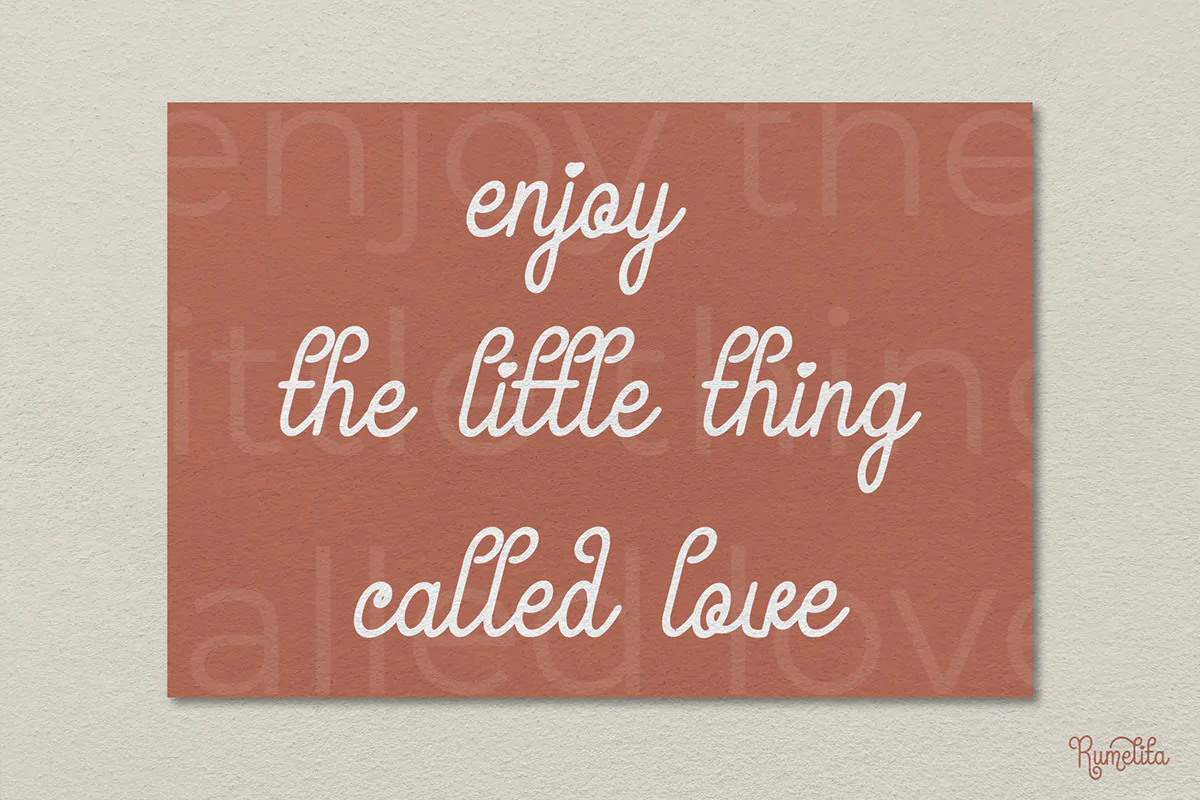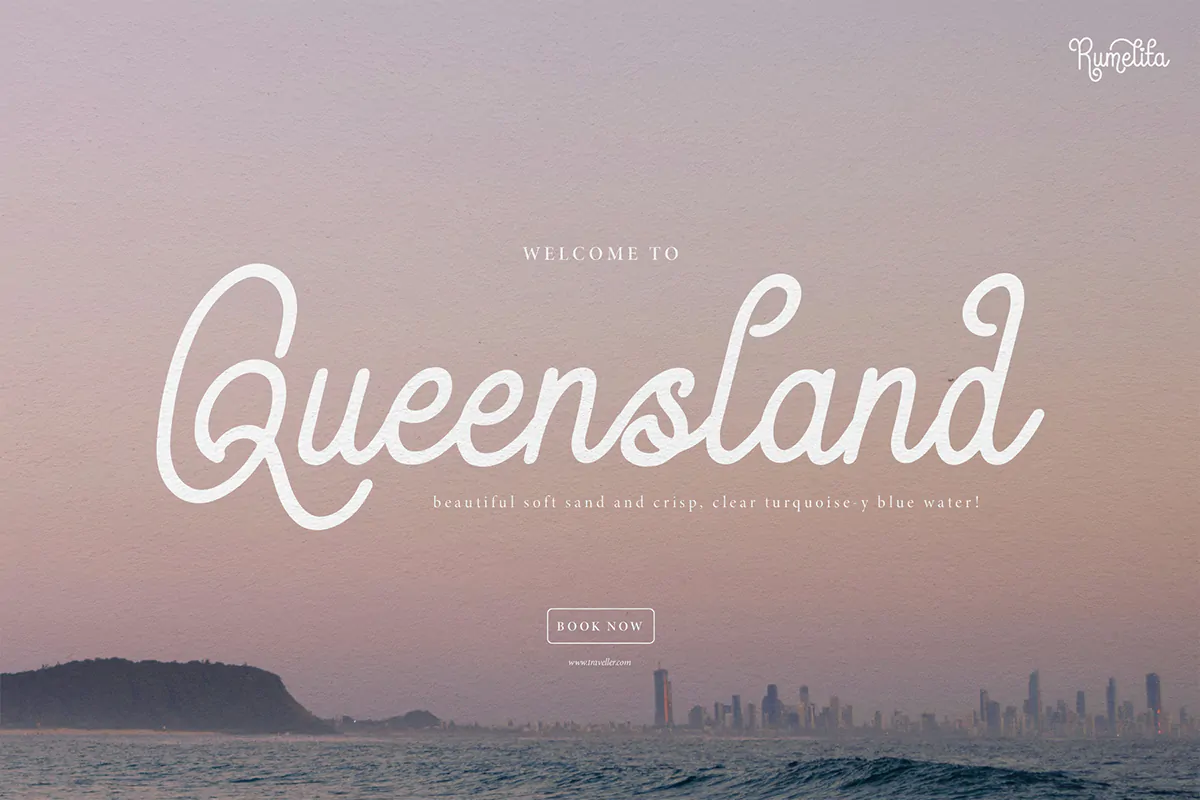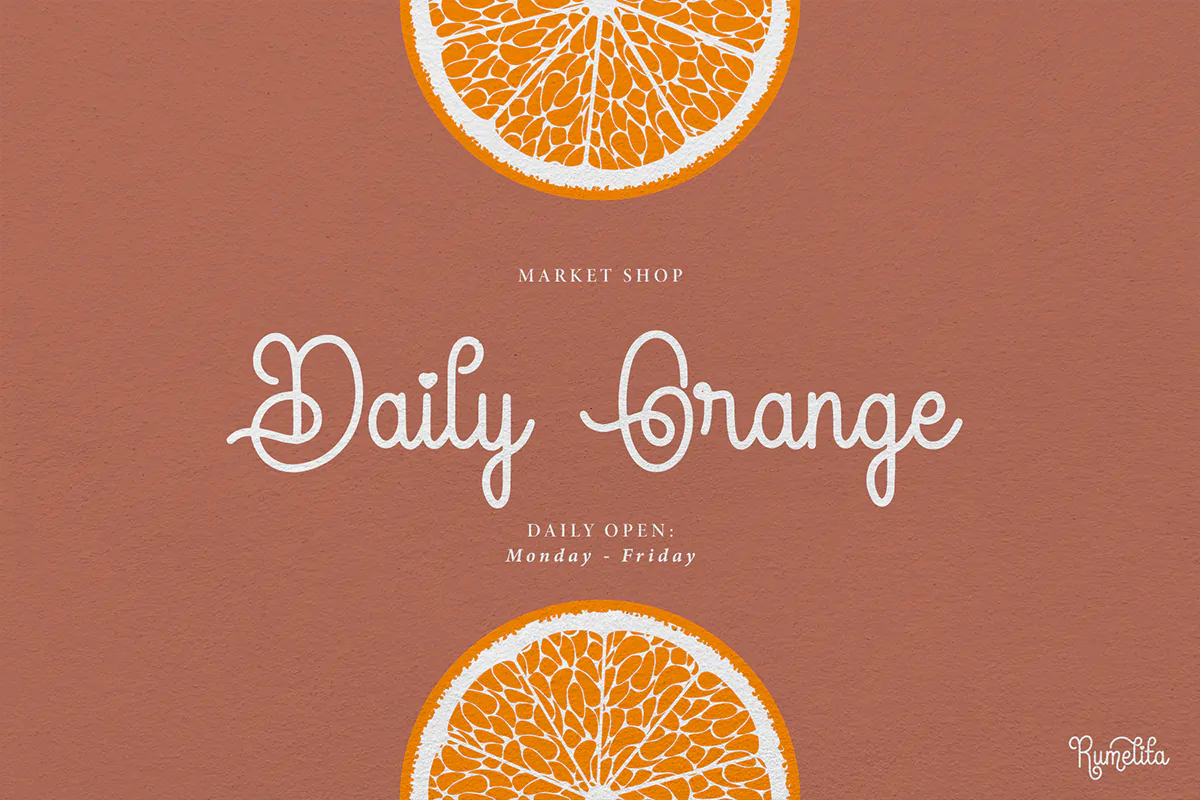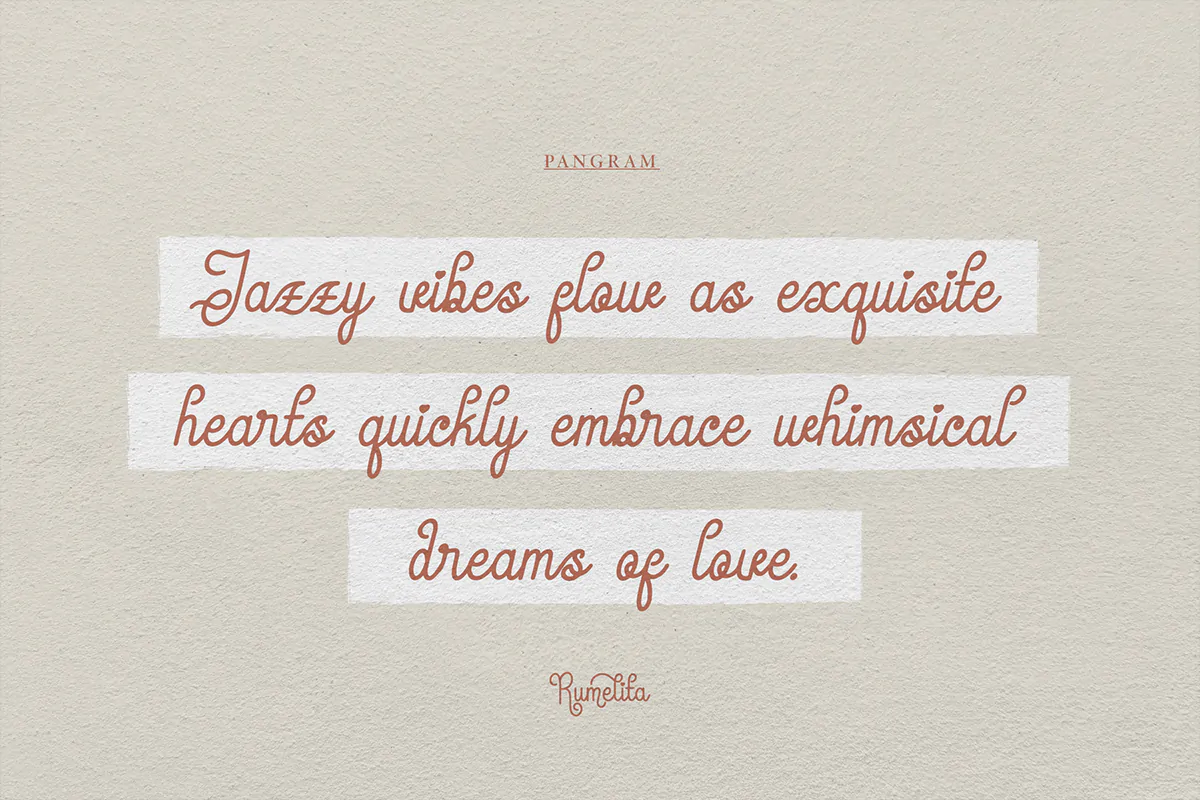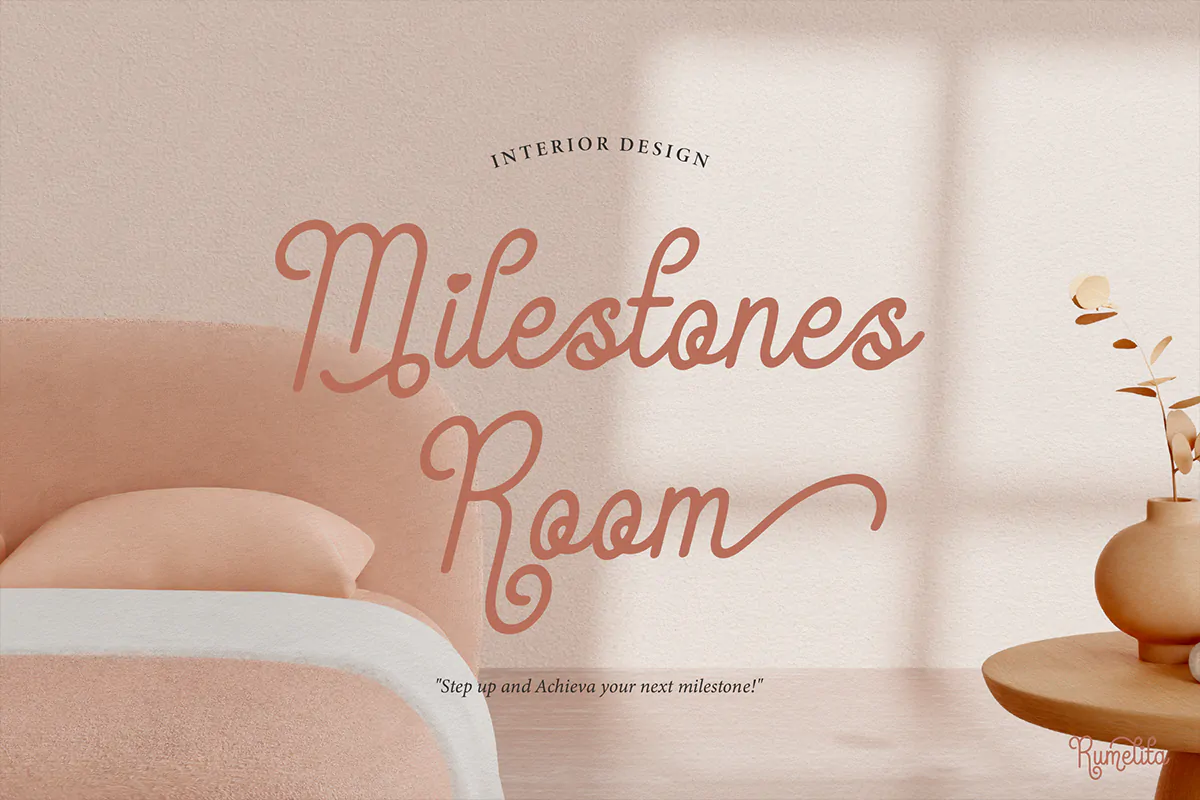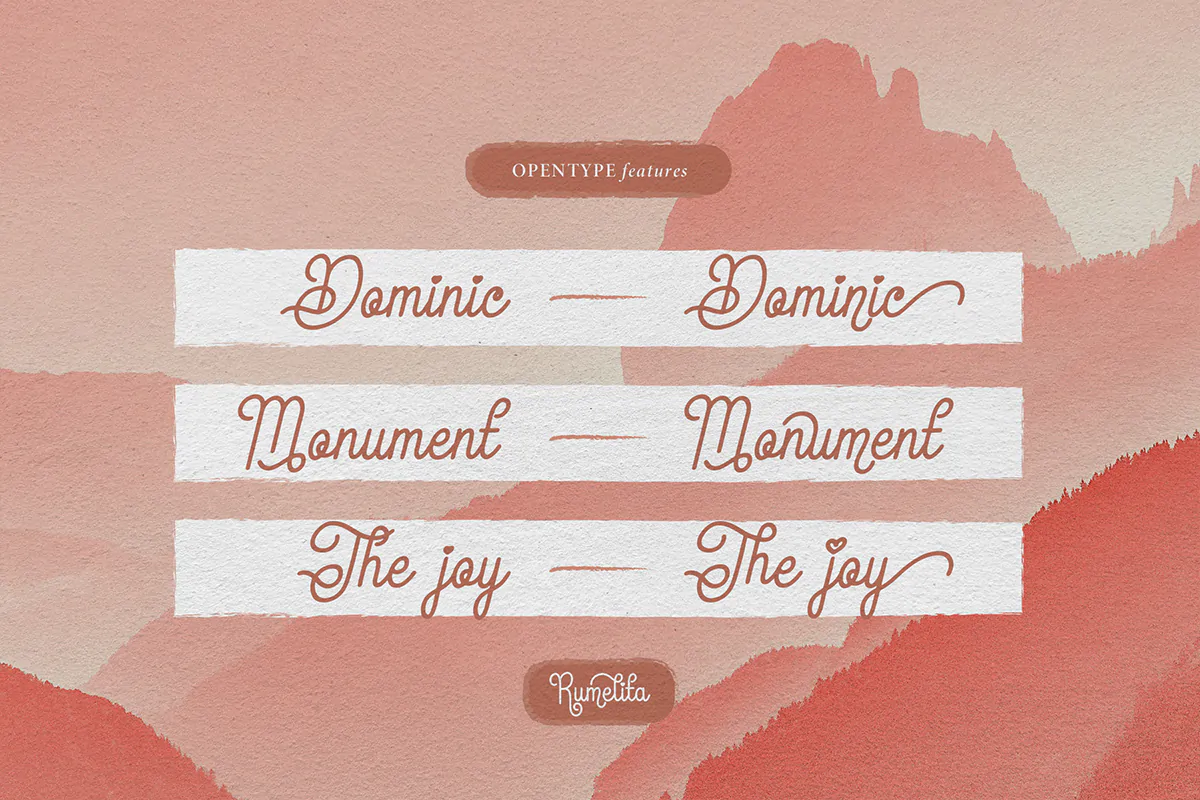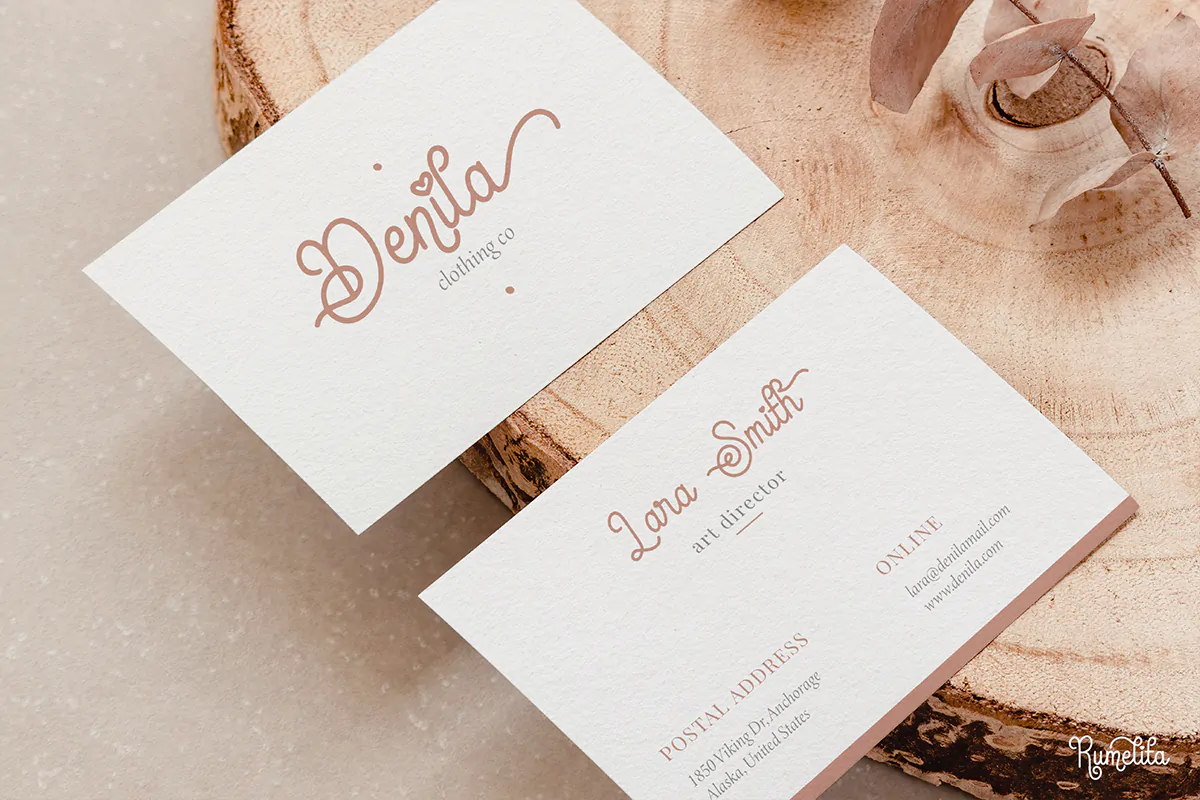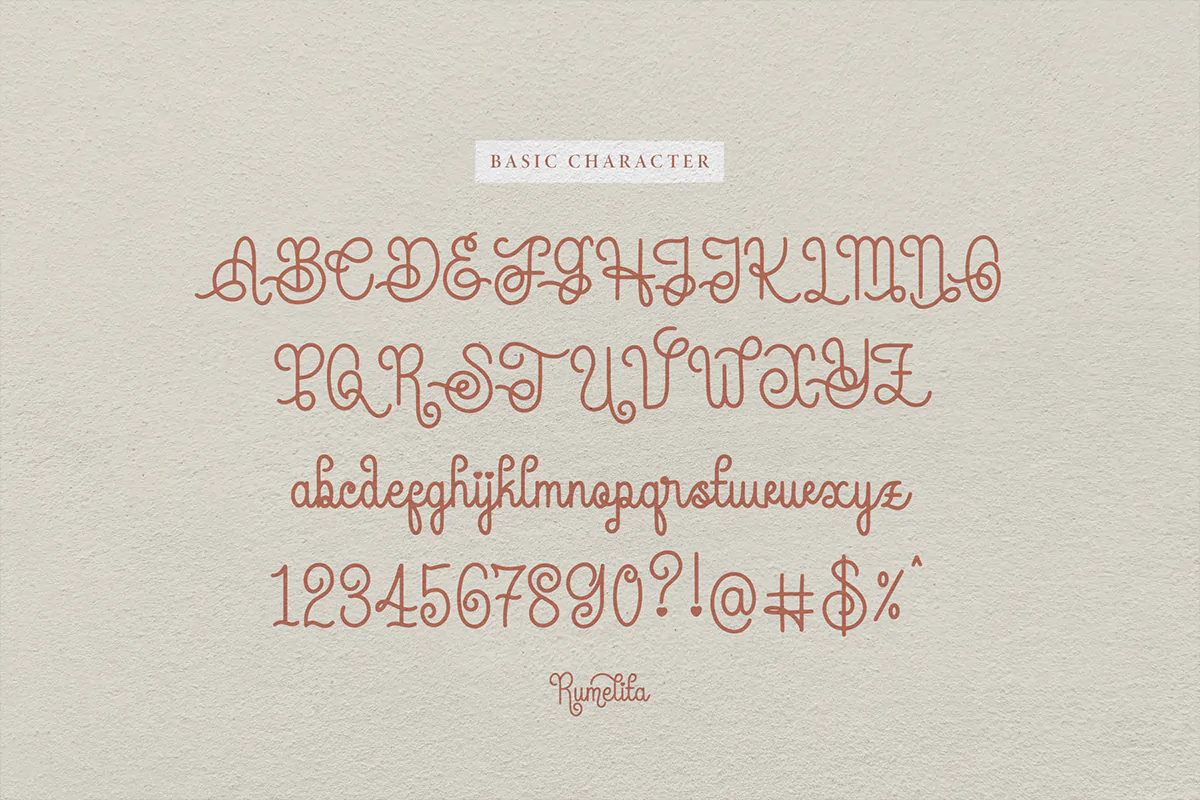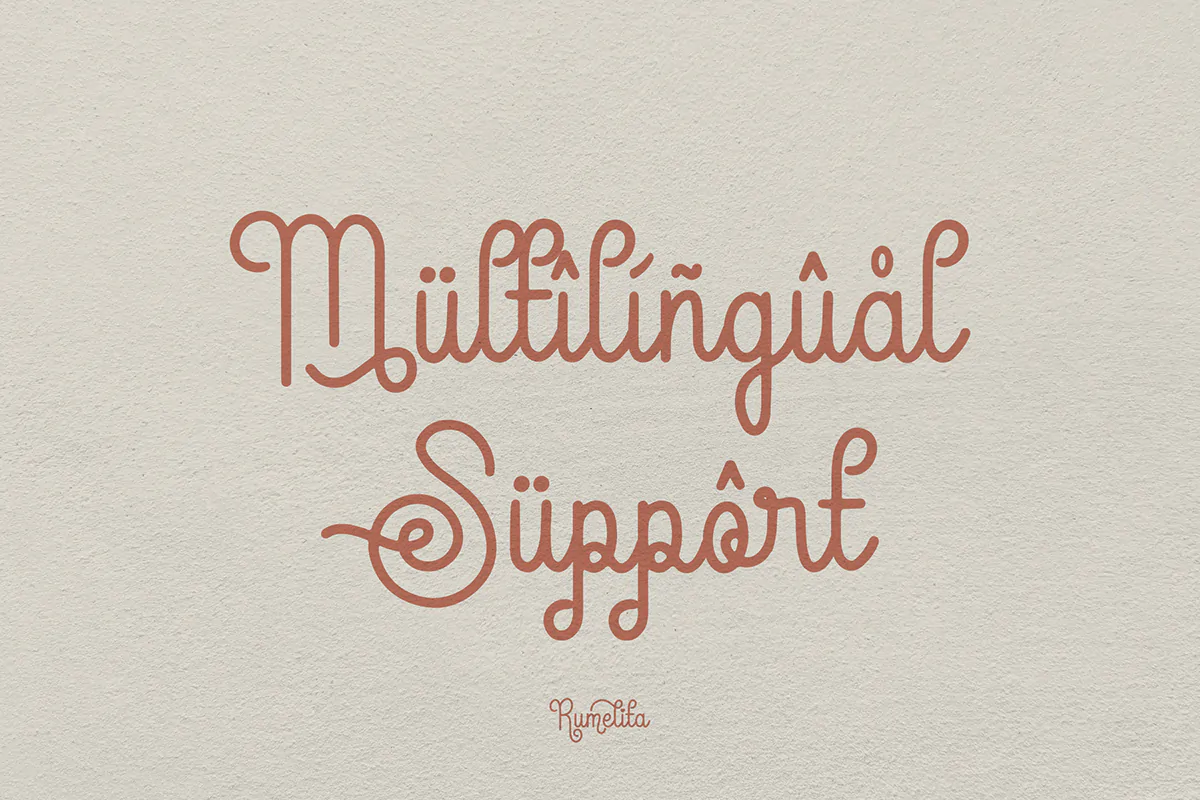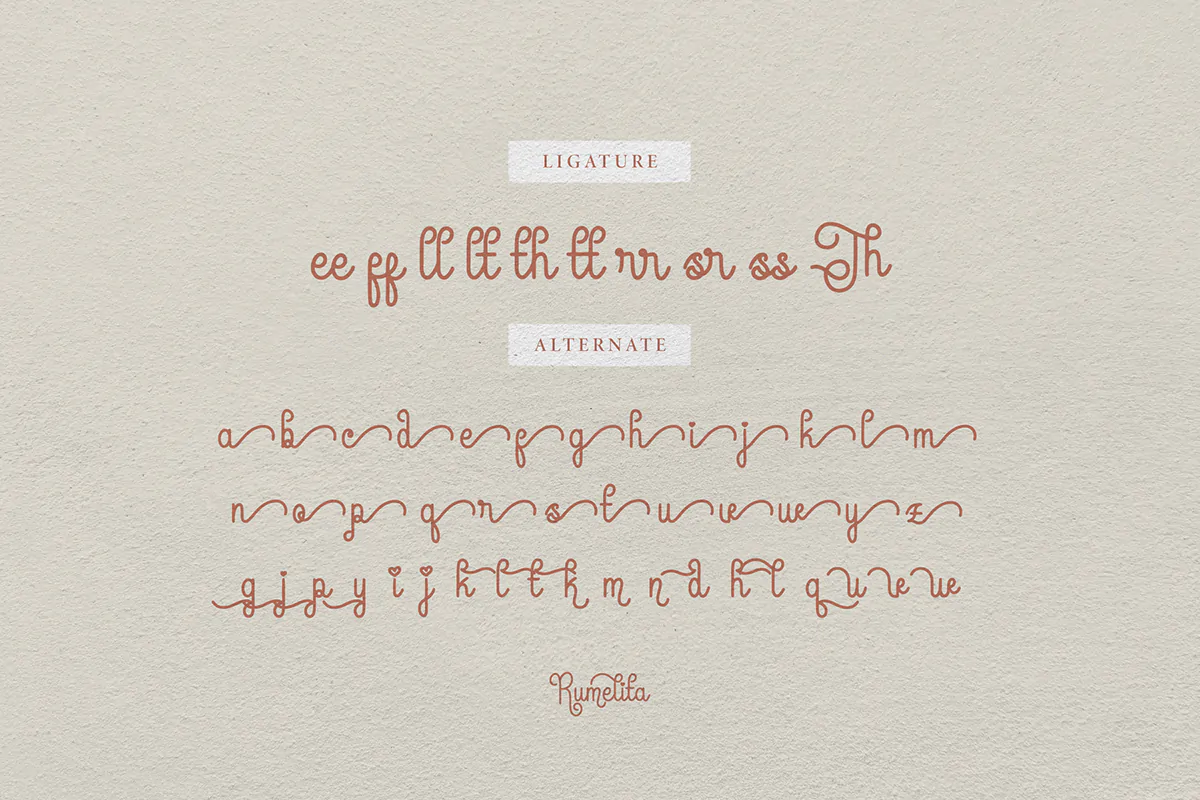
فونت دستنویس مونولاین Rumelita
فونت دستنویس مونولاین
فونت دستنویس مونولاین Rumelita یک قلم فوق العاده زیبای انگلیسی است که مناسب برای استفاده در طرحهای گرافیکی مختلف همچون طراحی انواع پوستر، تراکت، کارت ویزیت، بسته بندی محصولات و … میباشد.